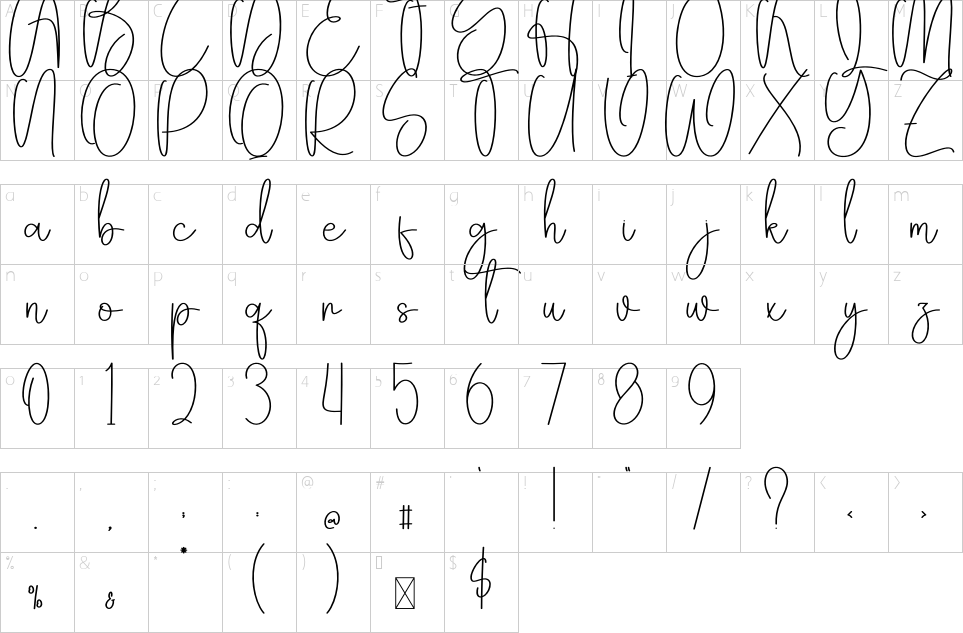
Generation Font – Download Grátis
Descubra a versão gratuita do “Generation Font” no seu Windows ou Mac. Esta elegante e minimalista fonte foi criada pelo designer scratchones, disponível para download 323 vezes e certamente vai enriquecer seus projetos digitais com um toque de originalidade. Com sua design simples e bem equilibrado, a “Generation Font” se destaca entre as opções gratuitas disponíveis hoje, oferecendo uma qualidade superior que pode ser facilmente integrada em vários formatos de documentos ou websites. Instale-a agora para experimentar o incrível poder da “Generation Font”.